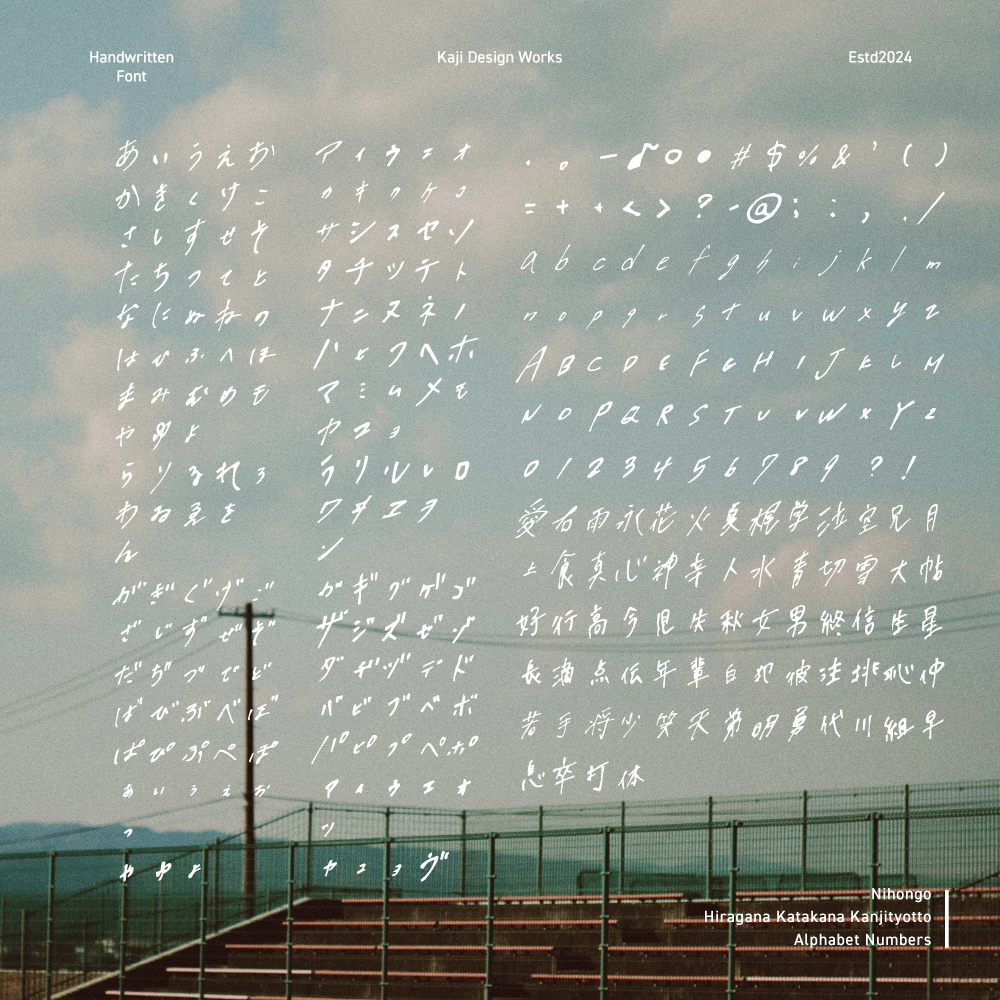
手書きフォント「みぎかたあがり」
ザクザク走り書きした右肩上がり手書きフォントです。 勢いで作ったのでガタガタゆるゆるしてますが、調整して使ってもらえると嬉しいです。 カジデザインのXアカウント(https://x.com/kajidesignlogo)をフォローで利用OK。 ご使用の名義のアカウント(作品などを公表されるアカウント)でフォローお願いします。 常識の範囲内でご自由にお使いください! 【収録内容】 ・TTFフォント ・ひらがな、カタカナ、数字、アルファベット、記号、漢字ちょこっと 【利用規約】 ・商用利用可能です。 (ご依頼での使用、ロゴ、動画、同人誌、成人向け作品での使用、変形・加工も問題ありません) ・再配布、譲渡、販売、商標登録は禁止です。 ・著作権は放棄していません。 ・本フォントをインストール、使用することで起こった、いかなるトラブル、不利益対して制作者は責任を負いません。 ご自身の責任でご使用ください。 またサポートもしておりませんので、お問い合わせはご遠慮ください。 ・予告なく内容、利用規約を変更する場合があります。 ・一部のOS、ソフトウェアでは使用できない場合がございます。 サムネイル画像:ぱくたそ様(http://www.pakutaso.com)